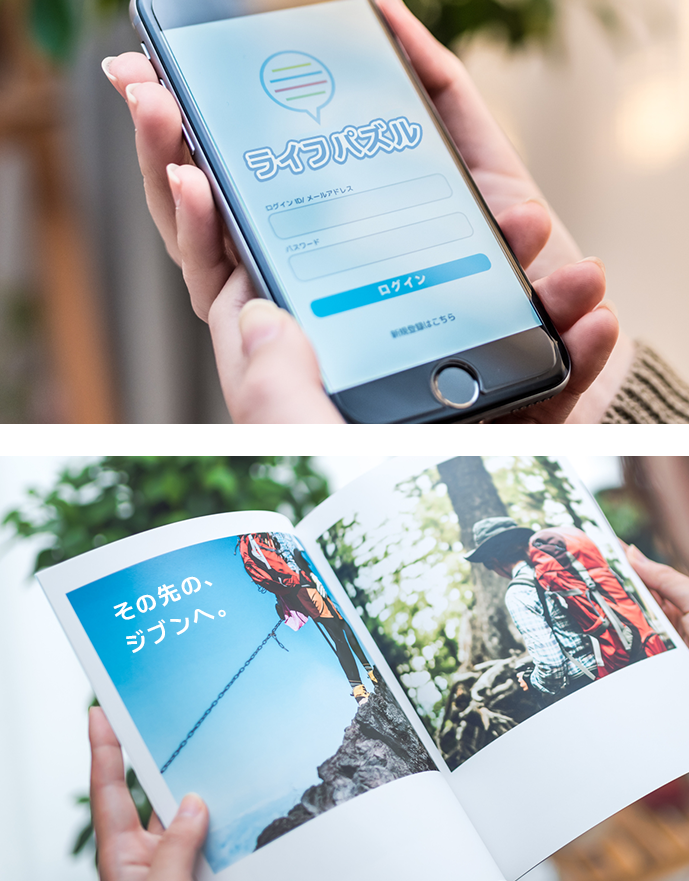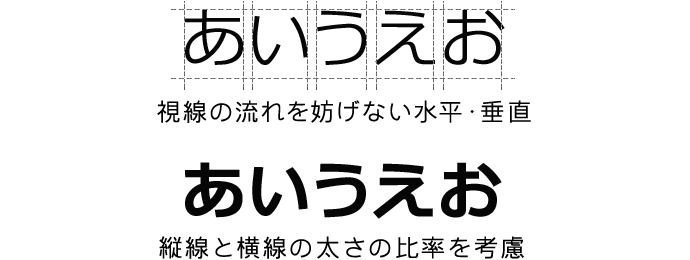
NIS_UDゴシックシリーズ
どなたにも親しみやすい、クセのないフォーマルな書体です。デザイン性を全面に押し出し過ぎることなく、あらゆる場所や媒体での利用において、視認性・判読性が高く、読み手にとってより自然で優しいフォントに仕上げています。
主な特長
横組が主流の現在において、より横組に適した設計思想とシンプルでクリアなデザインが大きな特長です。ふところは広めにし、縦線と横線の太さの比率を考慮。さらに横への視線流れを妨げない水平・垂直を基本としています。正方形の枠の中に一文字ずつデザインするという従来の発想から脱却し、左右の文字に配慮した欧文フォントの設計思想とベースラインを中心に横への流れを最大限考慮したデザインです。
開発背景
あらゆる媒体および制作環境のデジタル化に伴い、日本語の文字組においても横組が主流となりつつあります。UDフォントは、そんな横への自然な流れを最大限に配慮した『次世代汎用基本書体』という位置づけとして開発しました。
活用事例
あらゆる場所や媒体での利用において、視認性・判読性が高い優れたフォントです。